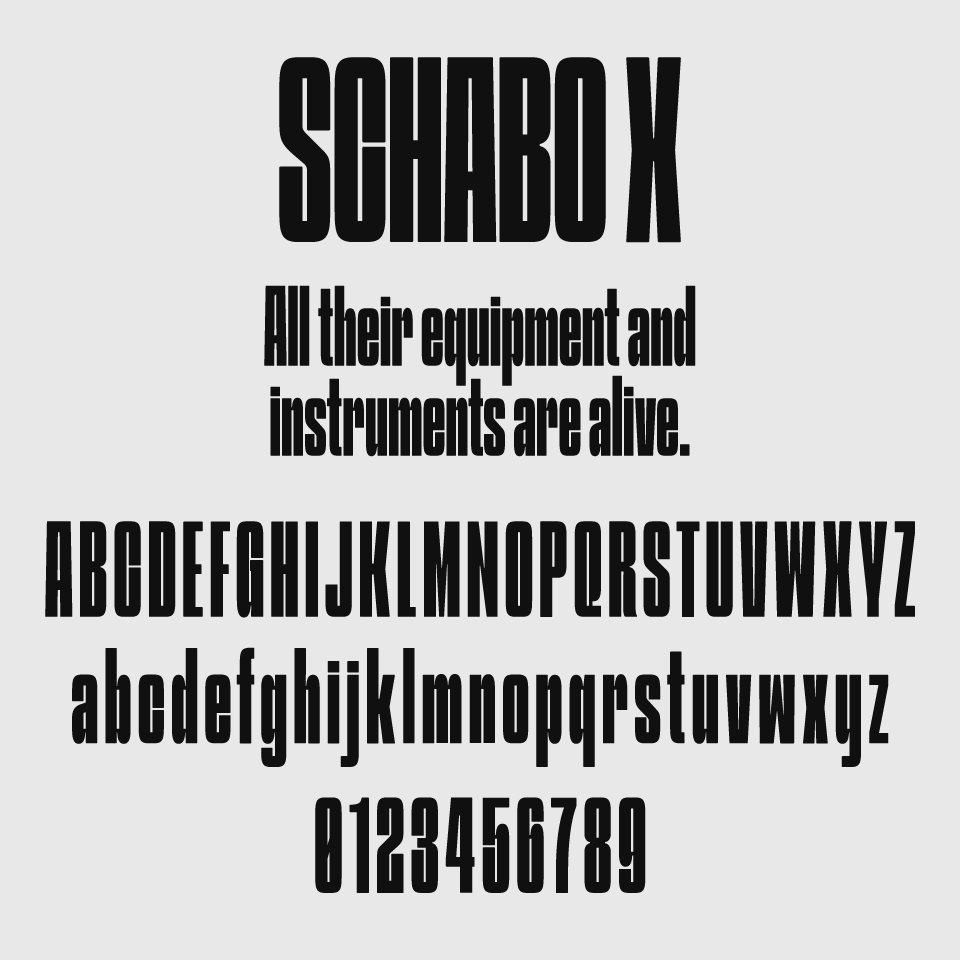
SCHABO X CONDENSEDフォントは、これでもか!と極端に縦長のシルエットと圧倒的なインパクトを持つフォントです。細く長く伸びた文字が他のフォントには見かけない独自の存在感を放ちます。
DINやIMPACTフォント以上に強く長体のシルエットは、シリアスでアバンギャルドな印象があり、モードやアート関連、実験的なデザインにぴったりです。奇抜さのなかにもスタイルがあり、挑戦的なビジュアル表現を求める場面で力強いアクセントになるフォントです。